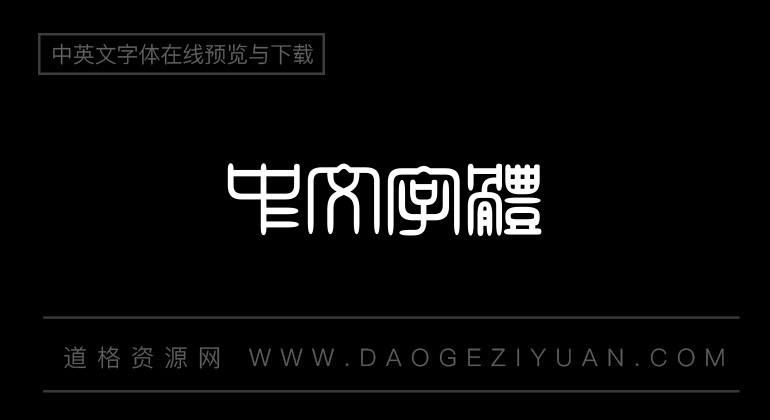
经典繁角篆字体是一种中国古典文字的字体,它是从汉代篆书发展而来的。繁角篆字体的结构特点是篆体笔画比较复杂,笔画的比例比较均匀,笔画的粗细比较均衡,笔画的结构比较规整,笔画的连接比较自然,笔画的结构比较精细,笔画的结构比较细腻,笔画的结构比较精致,笔画的折线比较圆滑,笔画的角度比较尖锐,笔画的拐角比较尖锐,笔画的穿插比较密集,笔画的连接比较紧凑,笔画的收尾比较精致,笔画的组合比较美观,笔画的结构比较完整。文件名:JingDianFanJiaoZhuan-1.ttf
经典繁角篆是一款非常不错的手写艺术字体,具有很好的视觉感,适合于文化类的宣传设计、商业类品牌的广告和产品包装设计以及个性化文字排版等较多场景。